我们知道,微软已经在今年早些时候宣布将会为Win10进行UI界面的大改进,在预览版中我们已经可以发现其中端倪,甚至是一些仍未生效的相关代码。
现在,根据Windows Lastest的报道,某些内部代码已经开始生效了,在Insider测试人员的手中,已经可以体验到了某些新外观的特性。
在最近的预览版中,Win10新界面有两个明显的特性显露。首先是圆角元素更加明显,另一个则是新图标。这些新的UI设计可以从应用程序、控制面板乃至文件管理器和各种窗口中都能观察到。
而对于更加基本的一些视觉元素,现在微软也开始着手修改了,例如微软就正在升级更新系统的字体。
当前,Win10默认的系统字体是“Segeo UI”,这在所有的应用程序,包括控制面板、浏览器、设置等等当中都被广泛使用。尽管Segeo UI很不错,但微软认为其仍有改进空间。
在未来的更新中,微软将会对其进行改进,增添一个“光轴”,这可以让字体能在各种外观尺寸上进行无缝缩放匹配。
一个很好的案例就是,微软似乎解决了小尺寸下字体的易读性问题,在不同的显示尺寸下,字体的轮廓都看着更出色。
与之相比,目前微软Win10的Segeo UI是以9pt大小的场景为基准设计的,字体在大尺寸下的表现以及过小的尺寸下的表现,都难以令人满意。
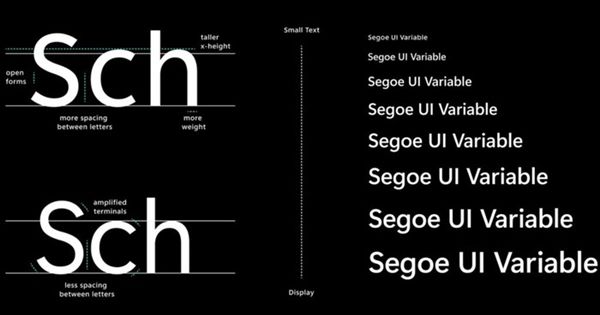
在下个版本的Win10中,微软会让Segeo UI动态适配各种App和设备,在不同的尺寸下都呈现出更好的易读性,在9pt以下的尺寸中尤为如此。同时,字体的形态和轮廓在大尺寸下也会有更好的表现。
就如上面的截图所示,App窗口标题栏的“Setting”字样在新字体设计的作用下,看起来会比现在字体样式更加清晰。
需要注意的是,微软目前正在逐步实装新的Segeo UI字体,它会随着时间推移应用到更多地方。
目前观察UWP应用的标题栏,是比较容易观察到新字体变化的,期待新版Win10的到来吧。